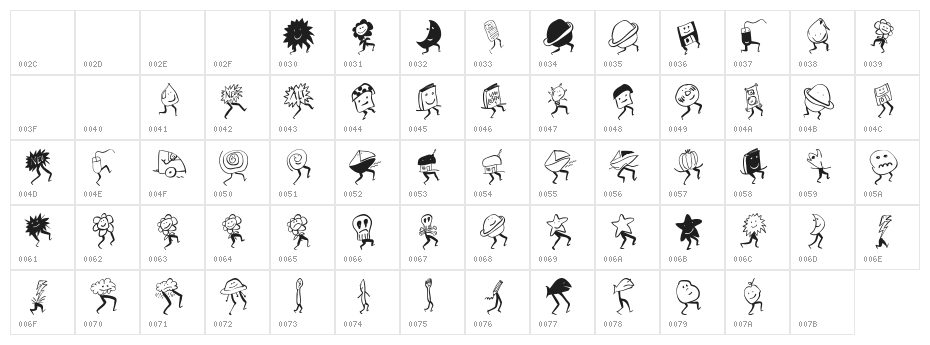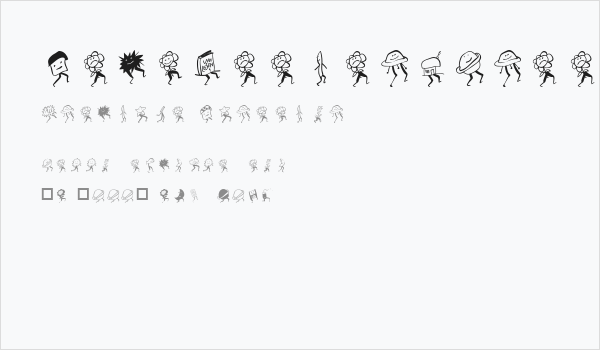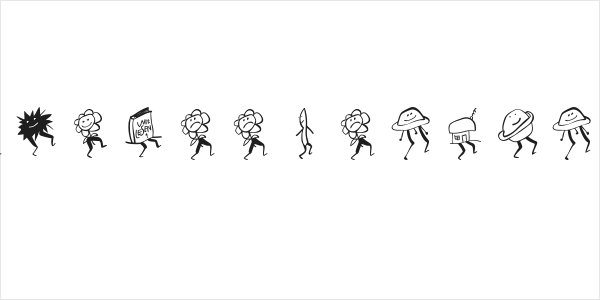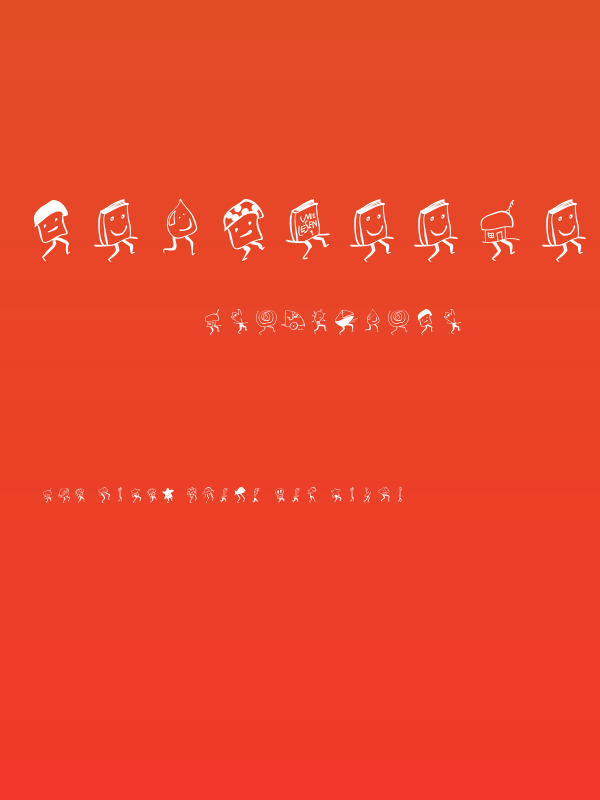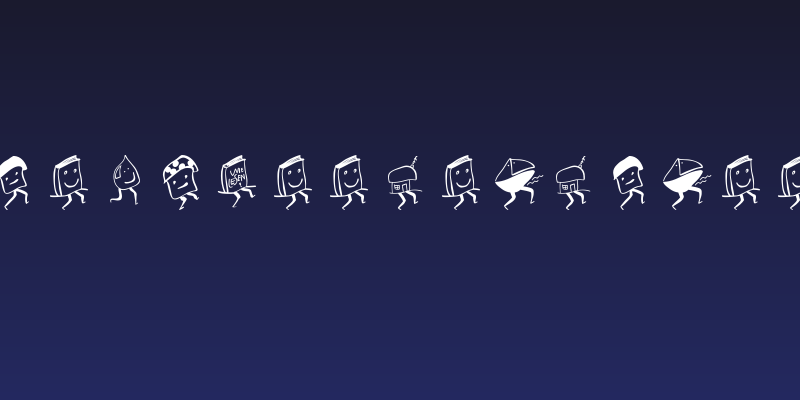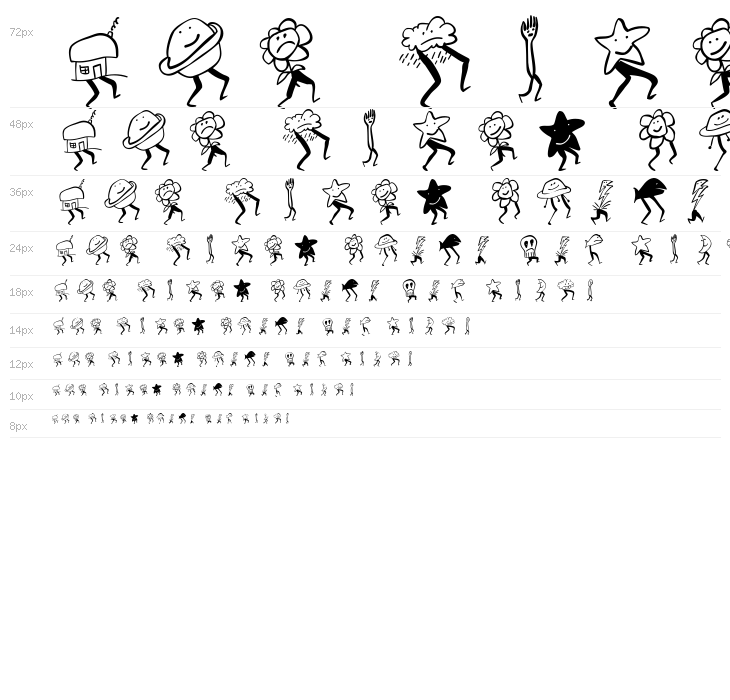
HeadFeeterThree Font
| Stile generale | Whimsical, Playful, Cartoonish |
| Caso d'uso | Decorative icons, embellishments, creative headings, visual storytelling. |
| Progetti proposti | Children's books, playful branding, party invitations, educational materials, comics, creative posters. |